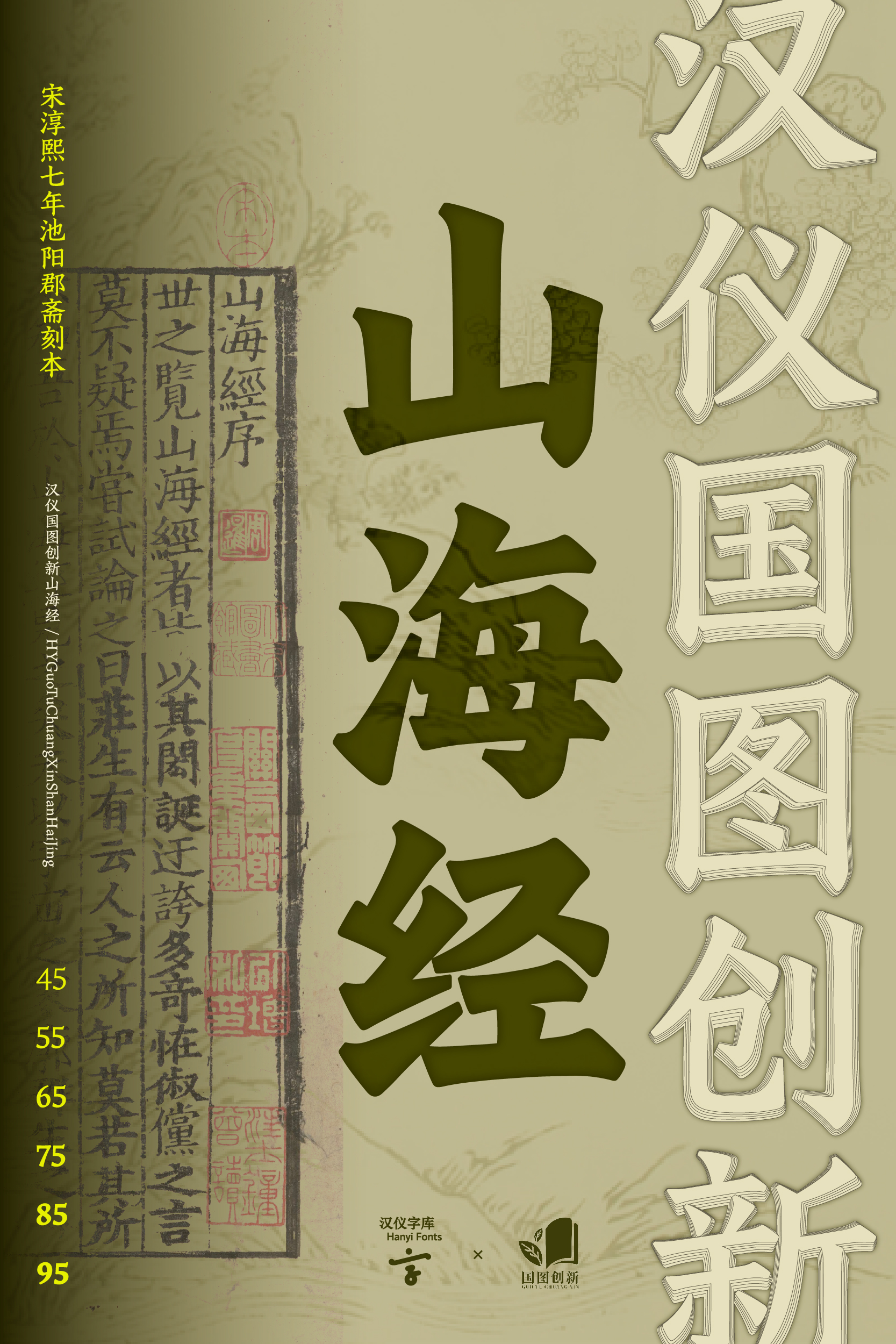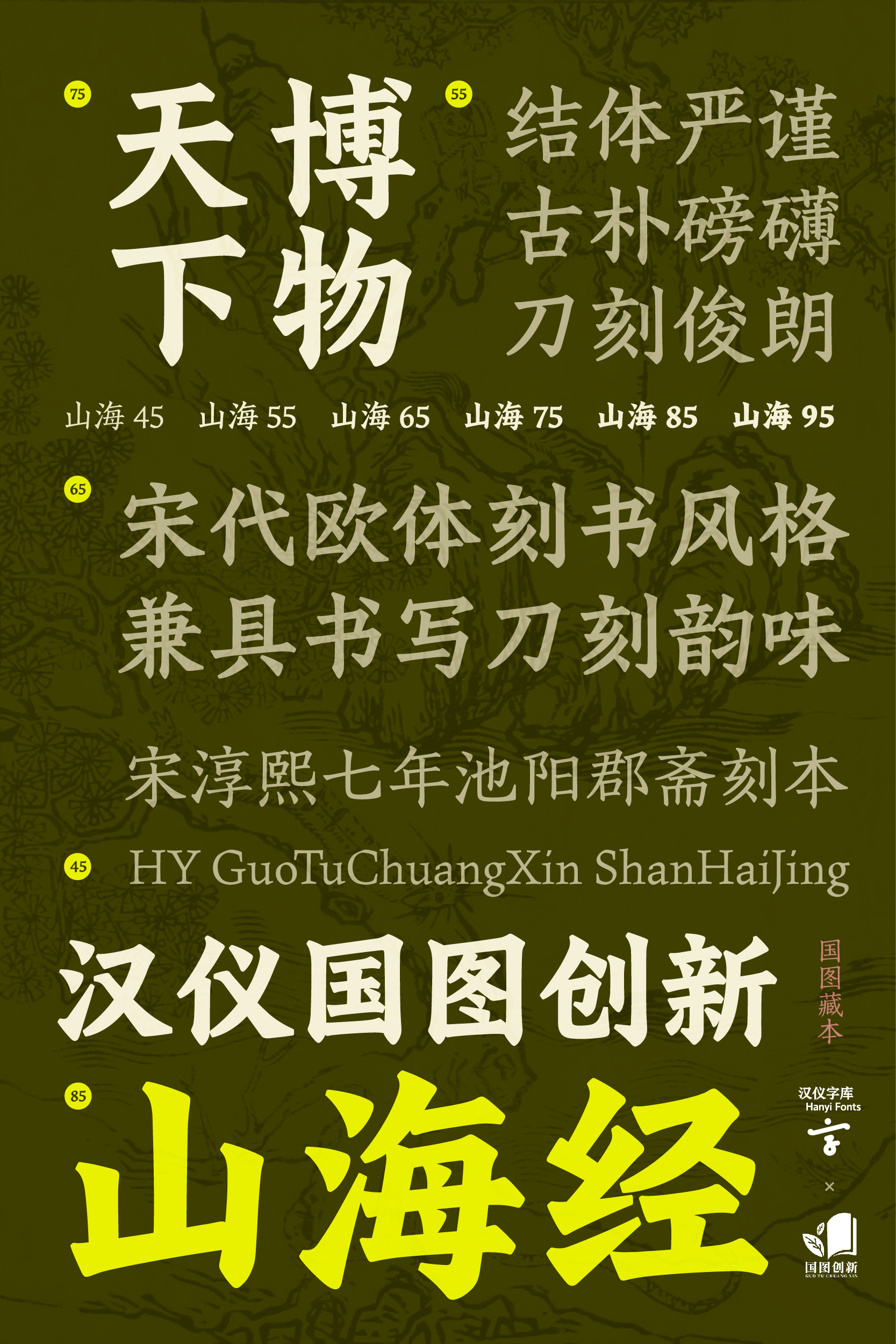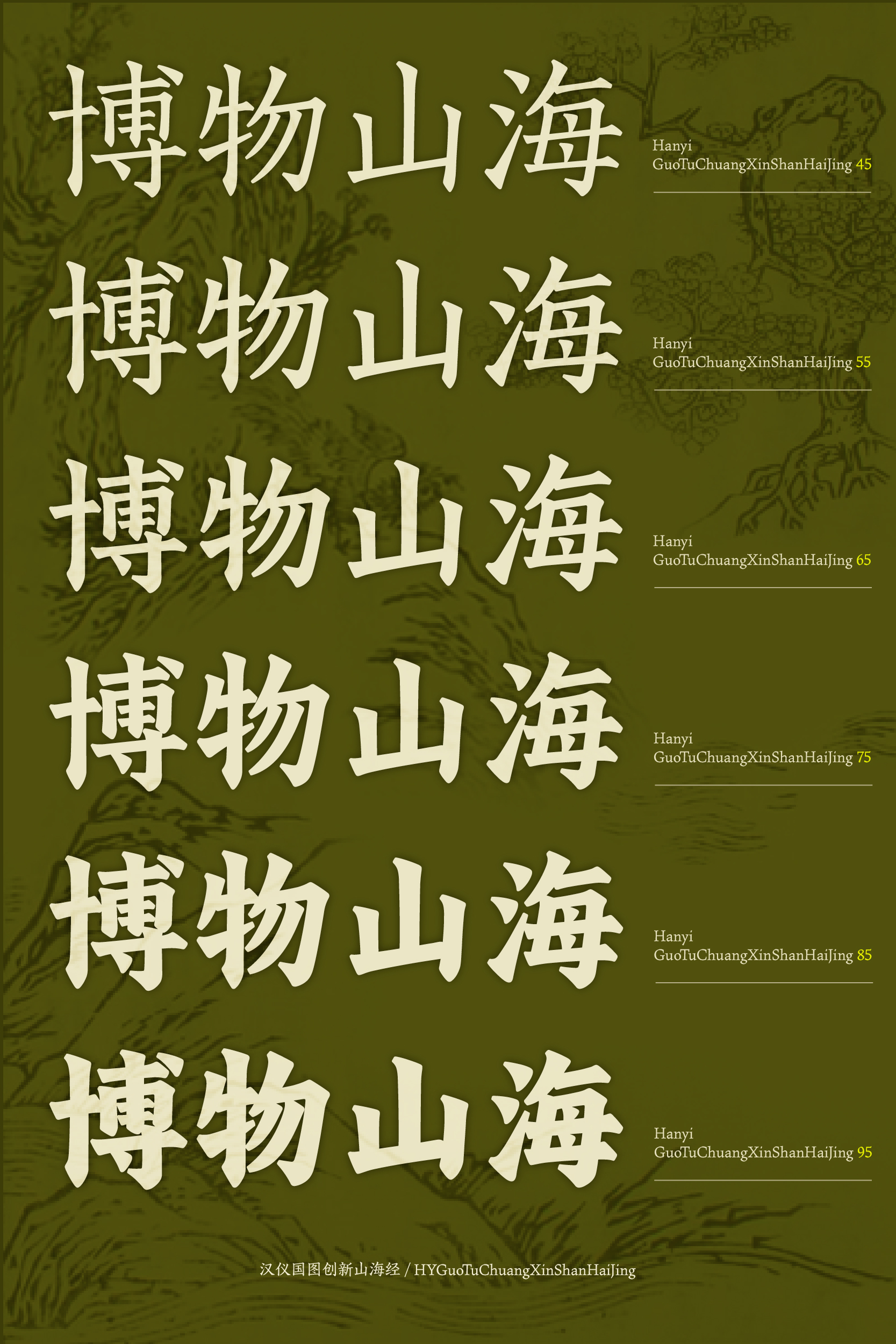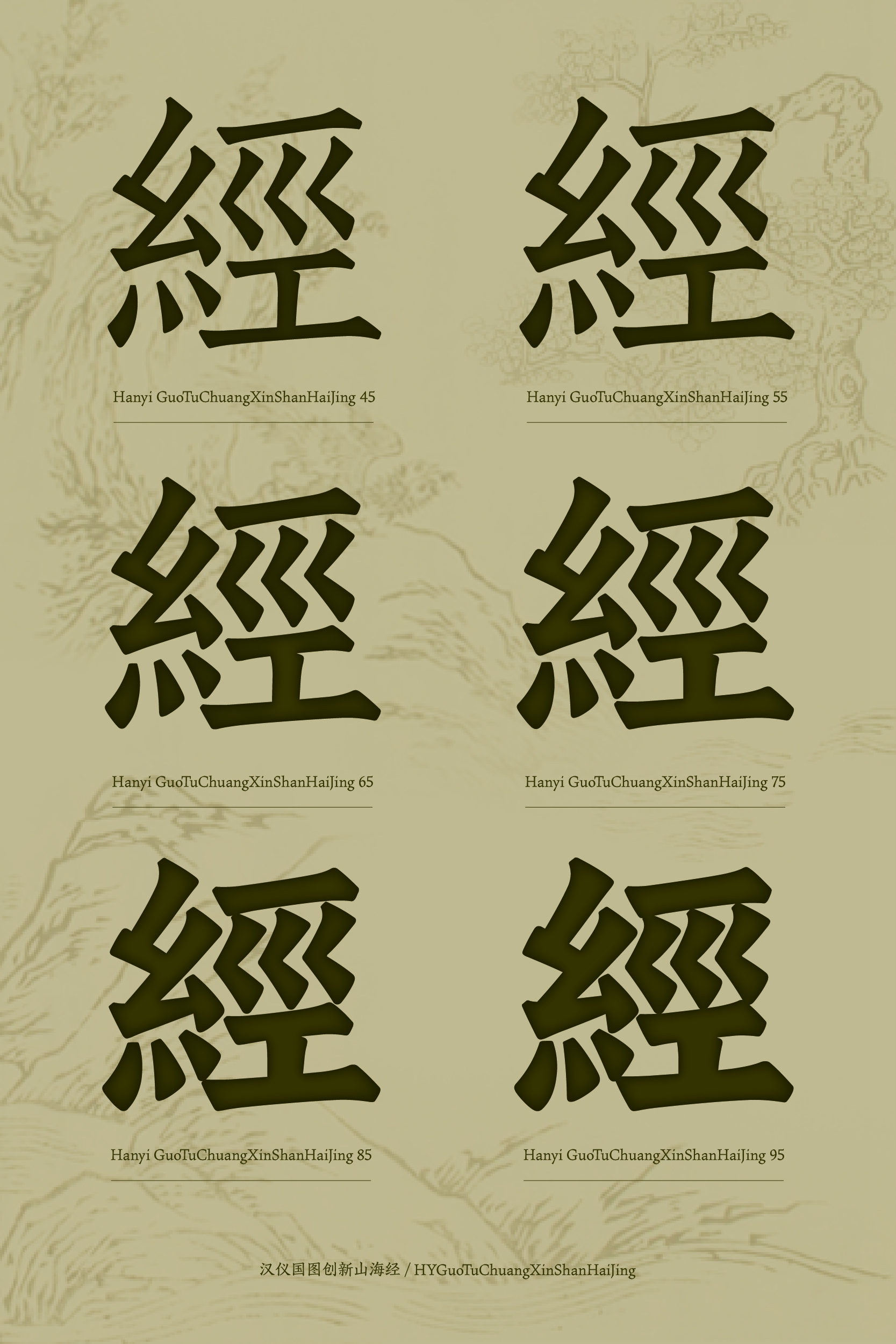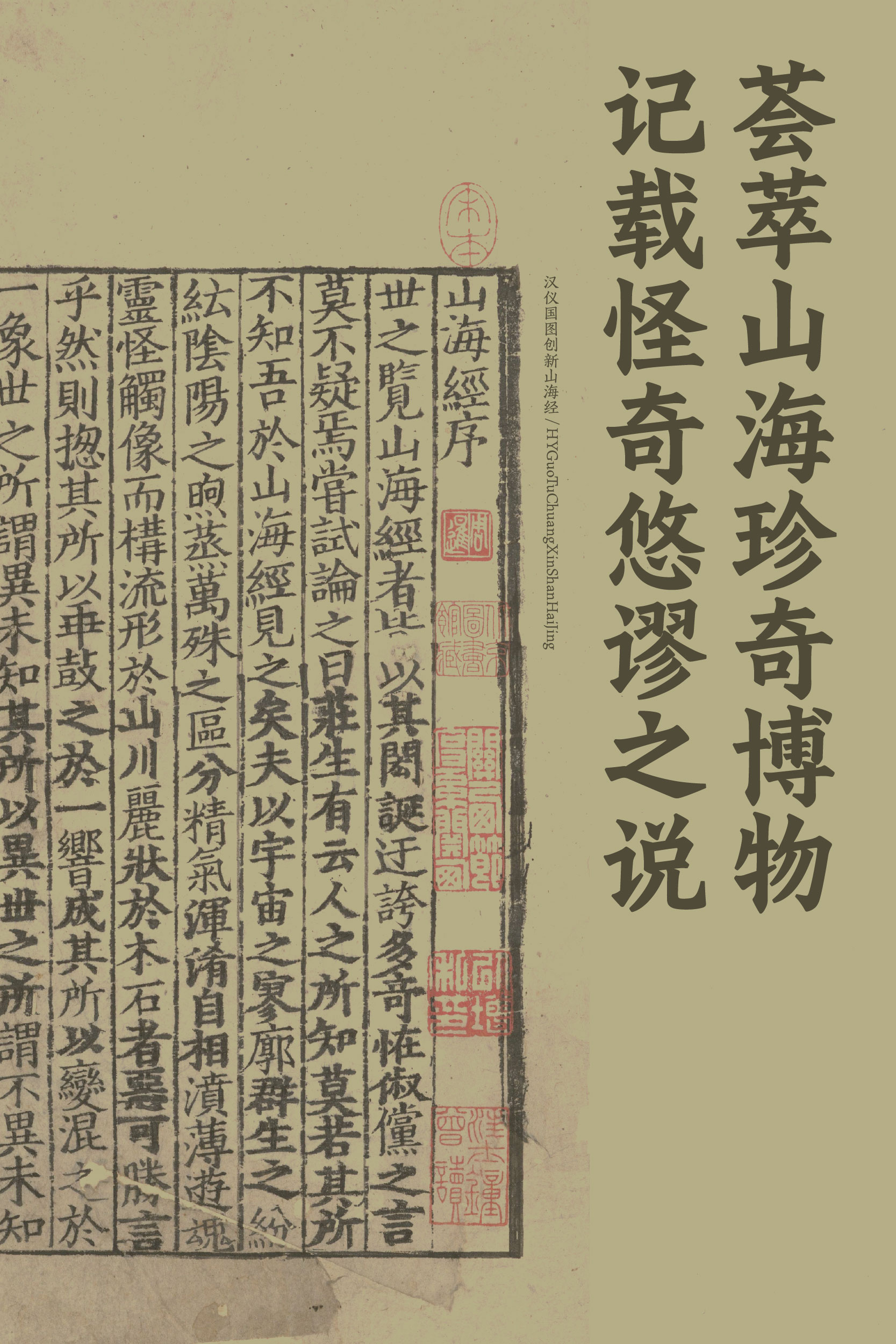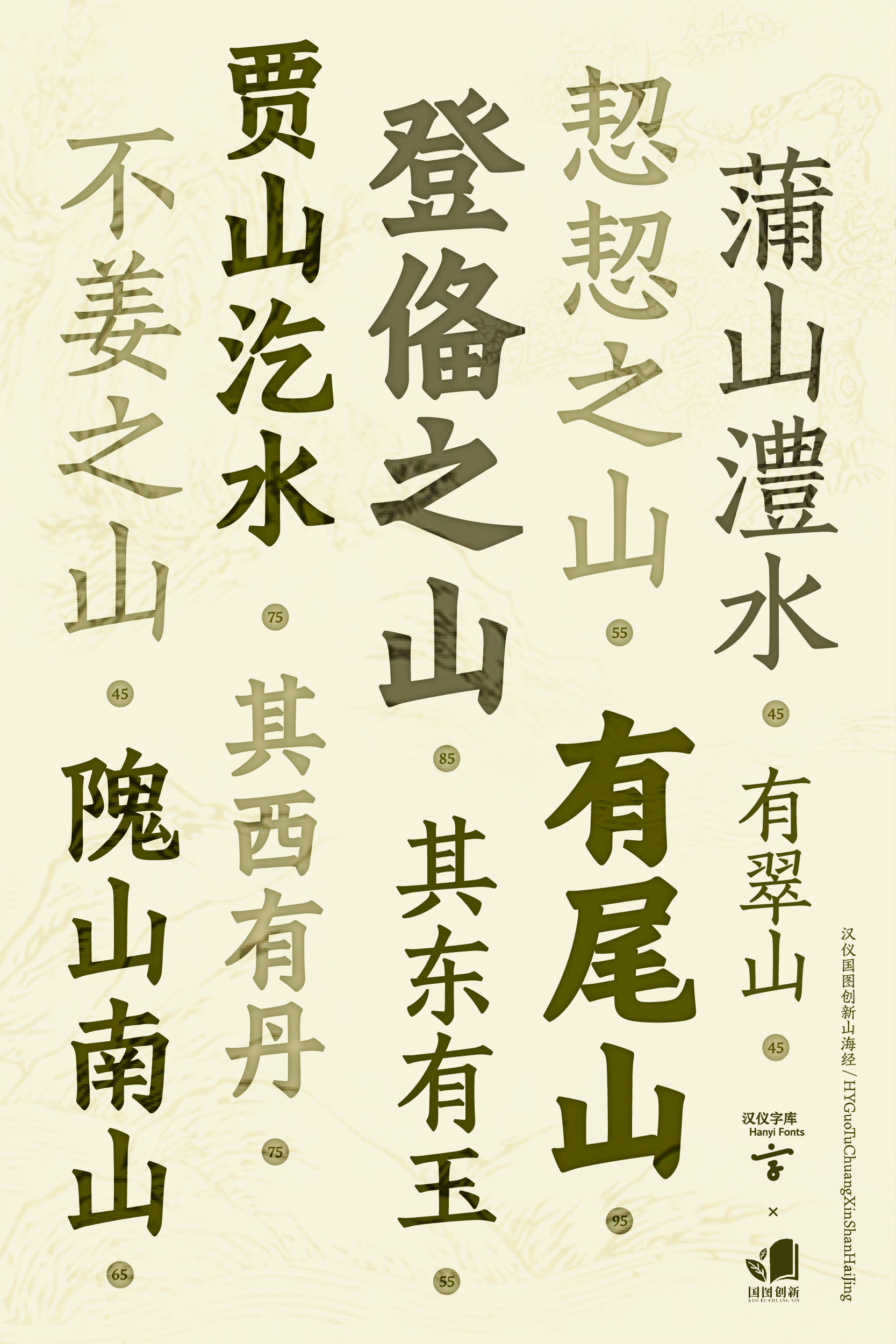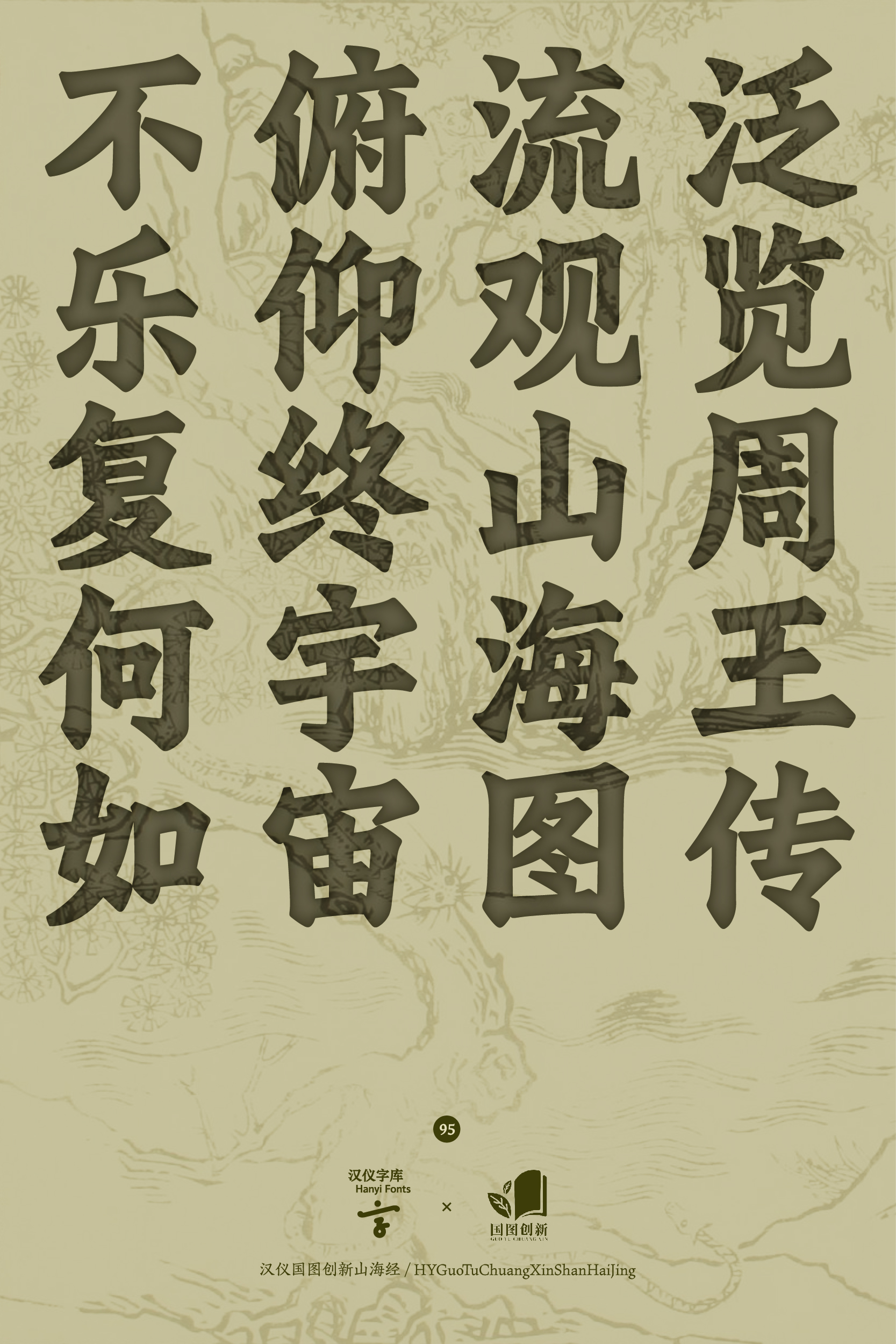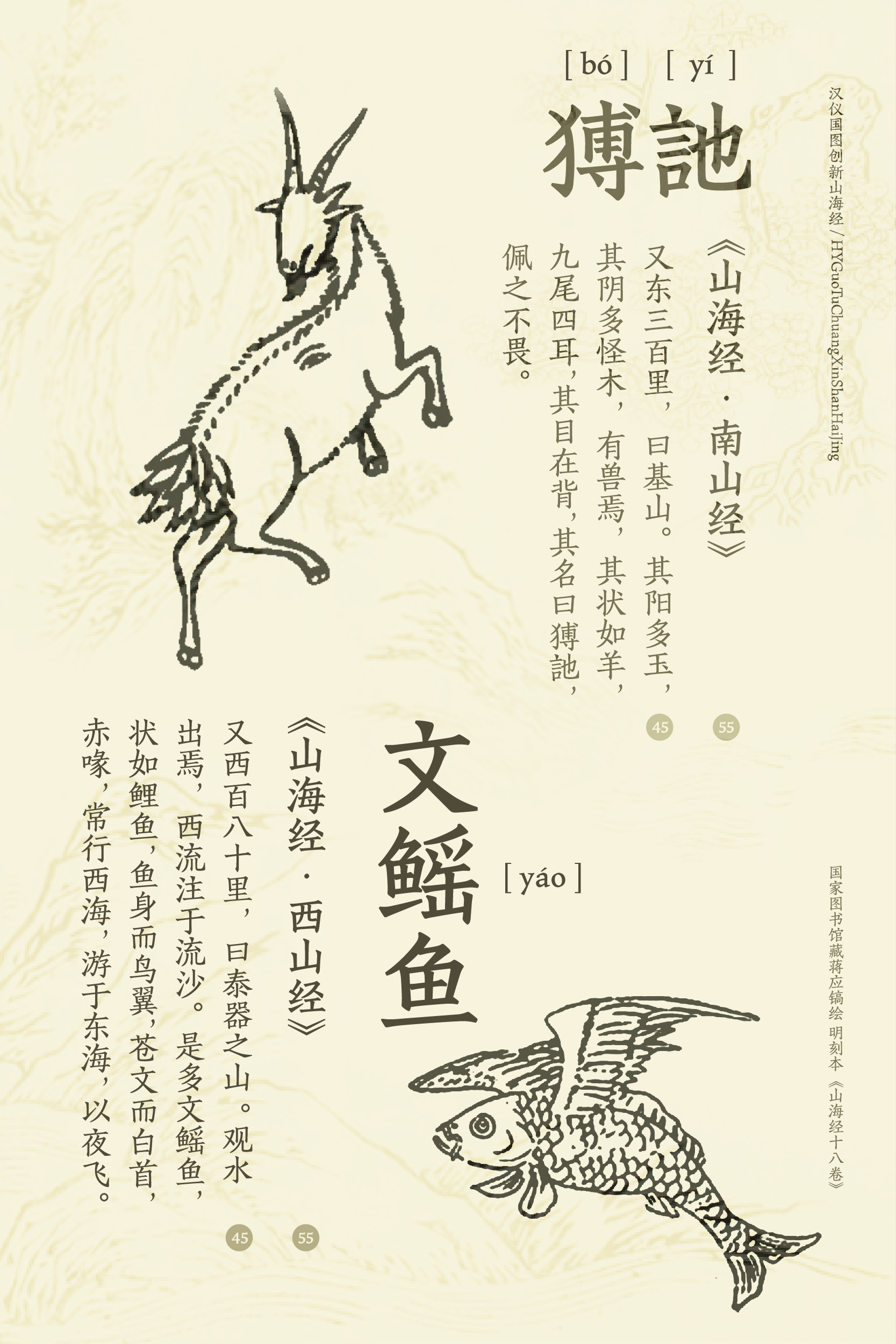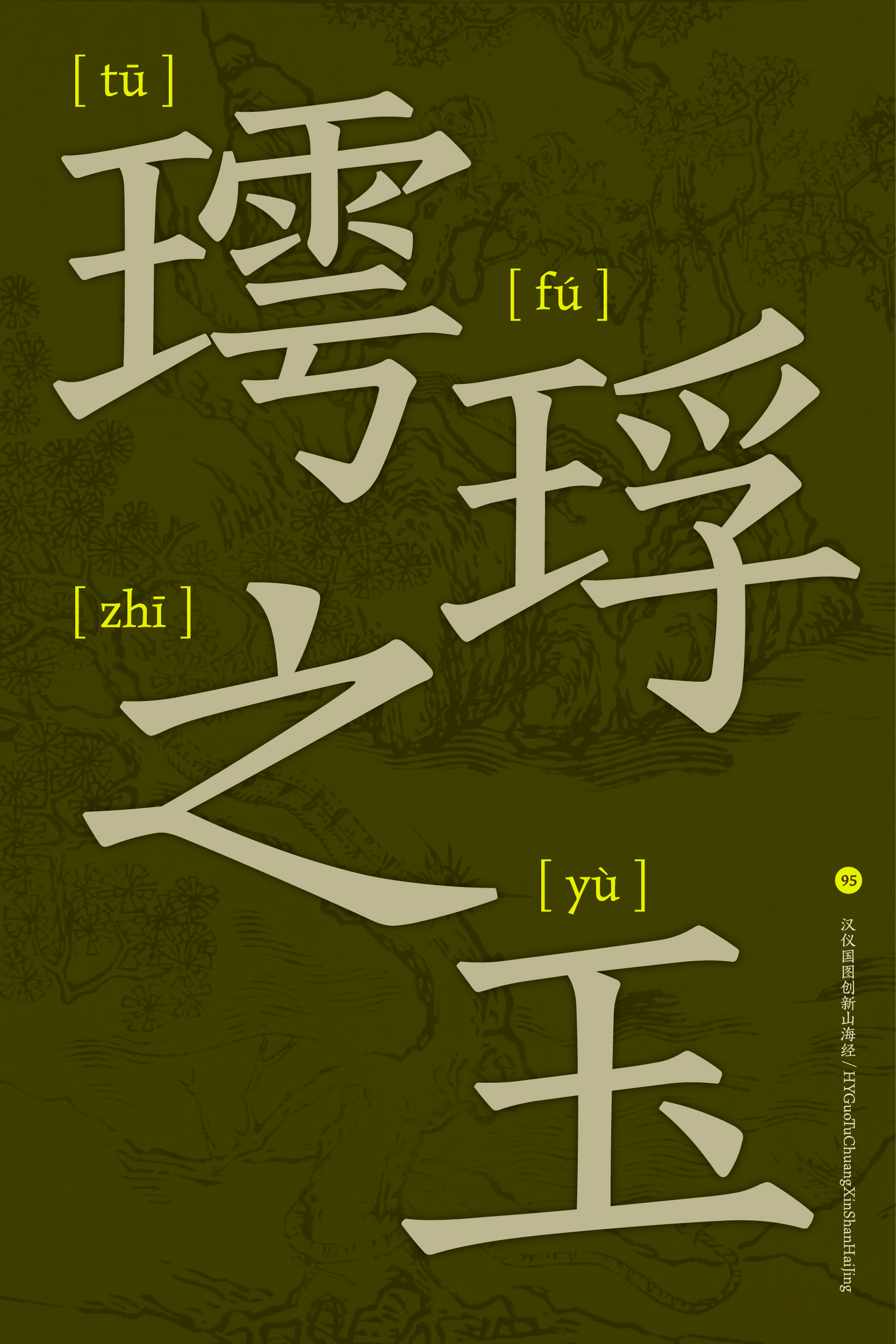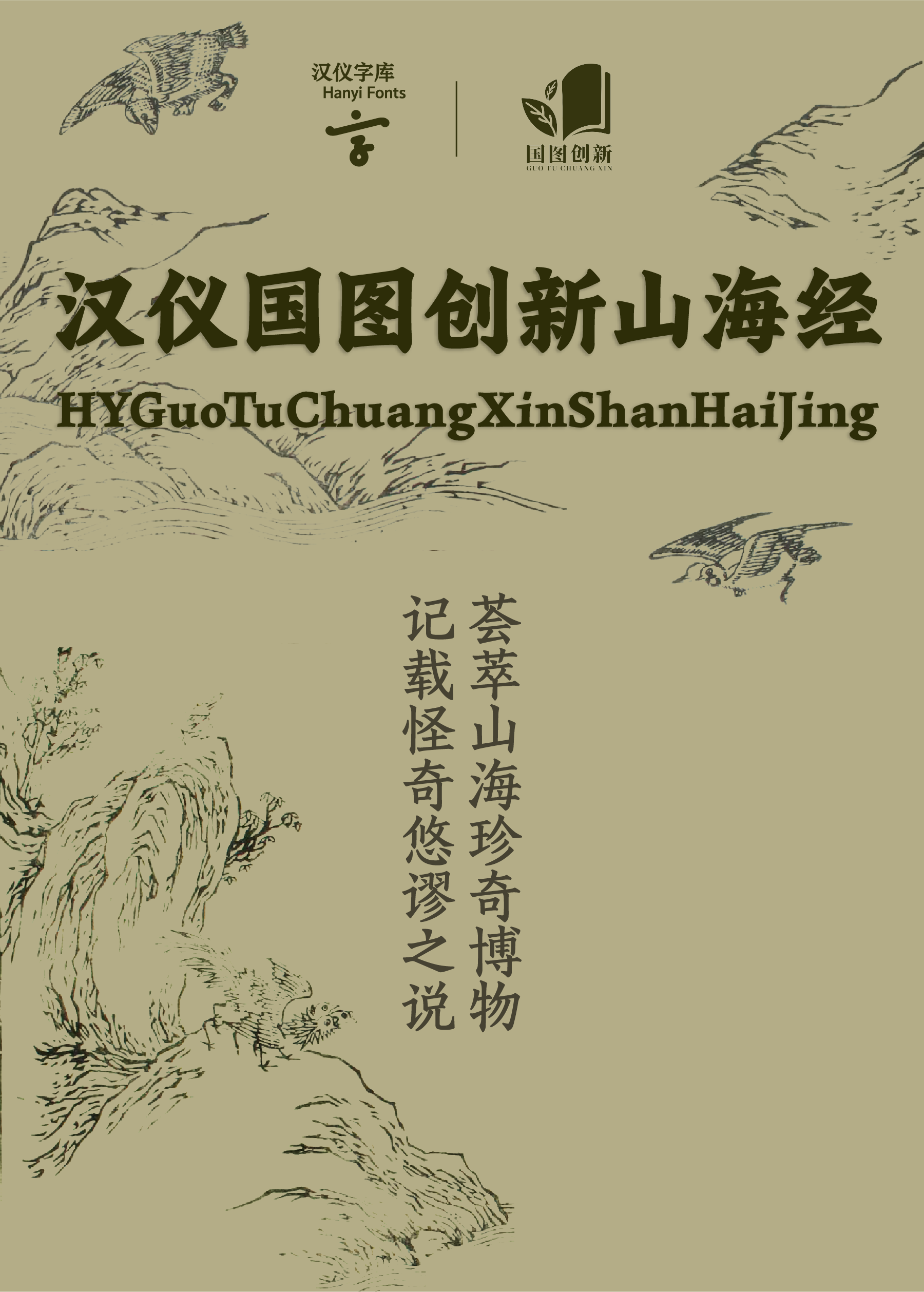
从山海经里走出来的字体
国家图书馆藏宋淳熙七年(公元1180年)池阳郡斋刻本《山海经》,是存世《山海经》年代最早的一部,此本传世孤罕,极为珍贵。
汉仪国图创新山海经,以此刻本作为蓝本,字形以宋代欧体刻书风格复刻,结体严谨,古朴磅礴,兼具楷书书写和刀刻 韵味。笔画起收平直,保留刀刻的俊朗;保留加锋的书写,书卷气浓郁。
这款刻本风格的字体还扩展成共有6个字重的家族字体,笔墨之间蕴含着山海奇谈物语,还原山海经古籍韵味。适用于古籍排版、文化艺术展览等使用场景。
汉仪字体产品研发中心对国图藏本宋刻池阳郡斋本《山海经》和明刻郭璞注、蒋应镐绘《山海经》两个版本做字体研究,最终选取池阳郡斋本进行汉仪国图创新山海经的创作蓝本。
汉仪国图创新山海经,字形轮廓以方形为基础,略微收窄。字形以宋代欧体刻书风格进行复刻,同时借鉴了楷书的部分笔形及字形结构;结体严谨,古朴磅礴,兼具楷书书写和刀刻韵味。
笔画整体起收平直,遵循原刻本的笔形风格。细体强调刀刻的俊朗,挺拔有锋芒;粗体的笔画起收笔保留加锋的书写方式,粗厚稳定,书卷气浓郁。
汉仪国图创新山海经的西文设计,字形比例关系参考了图拉真石柱大写字母,古典优雅。衬线结构强调了刀刻方向,轴线倾斜更具有人文感;数字取消上升部与下降部的设计,兼顾大写字母与小写字母搭配使用;中西文匹配强调刀刻楷书风格,彰显古朴磅礴气质。
汉仪国图创新山海经,扩展为共6个字重的家族字体。笔墨之间蕴含着山海奇谈物语,还原山海经古籍韵味。适用于古籍排版、文化艺术展览等使用场景。